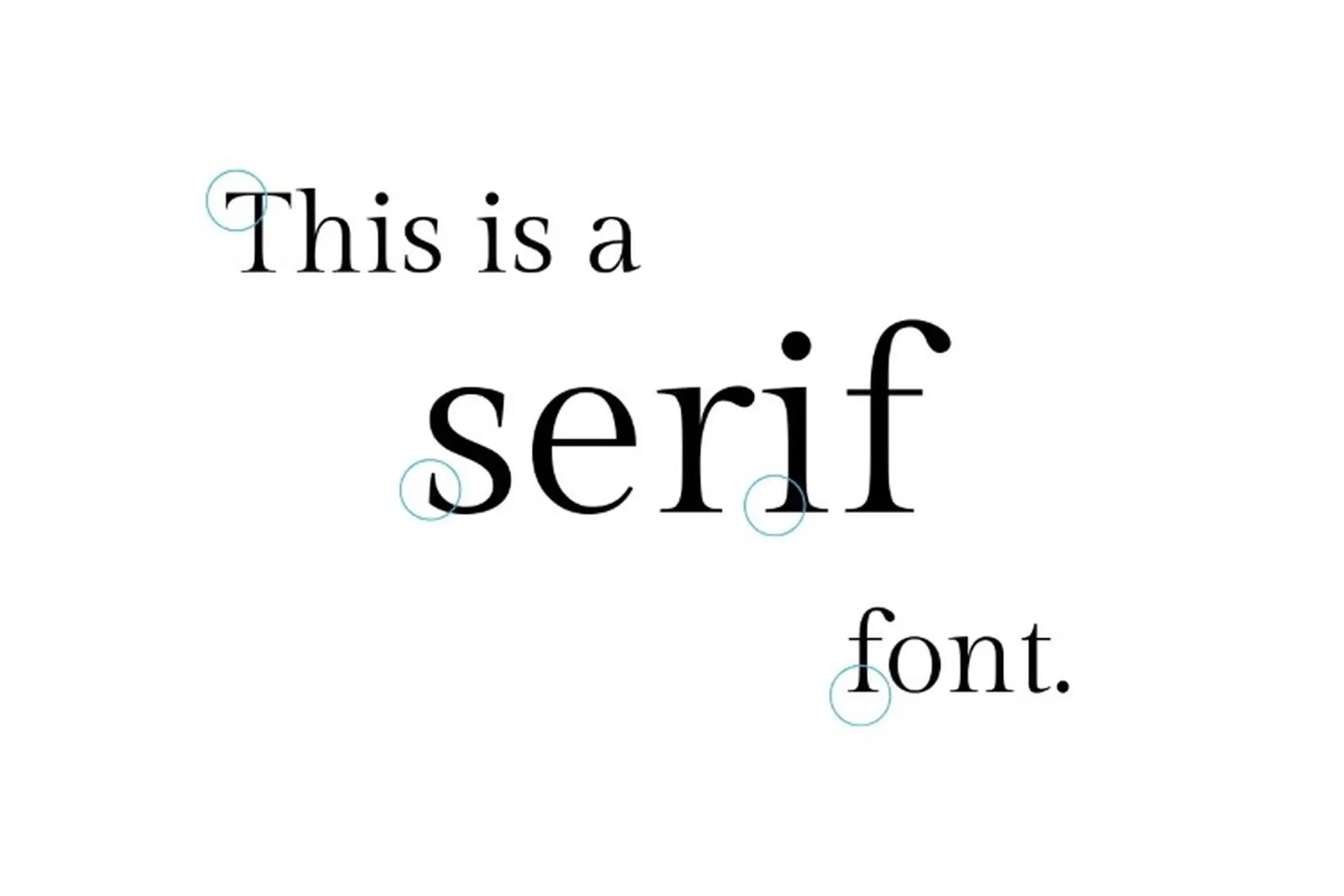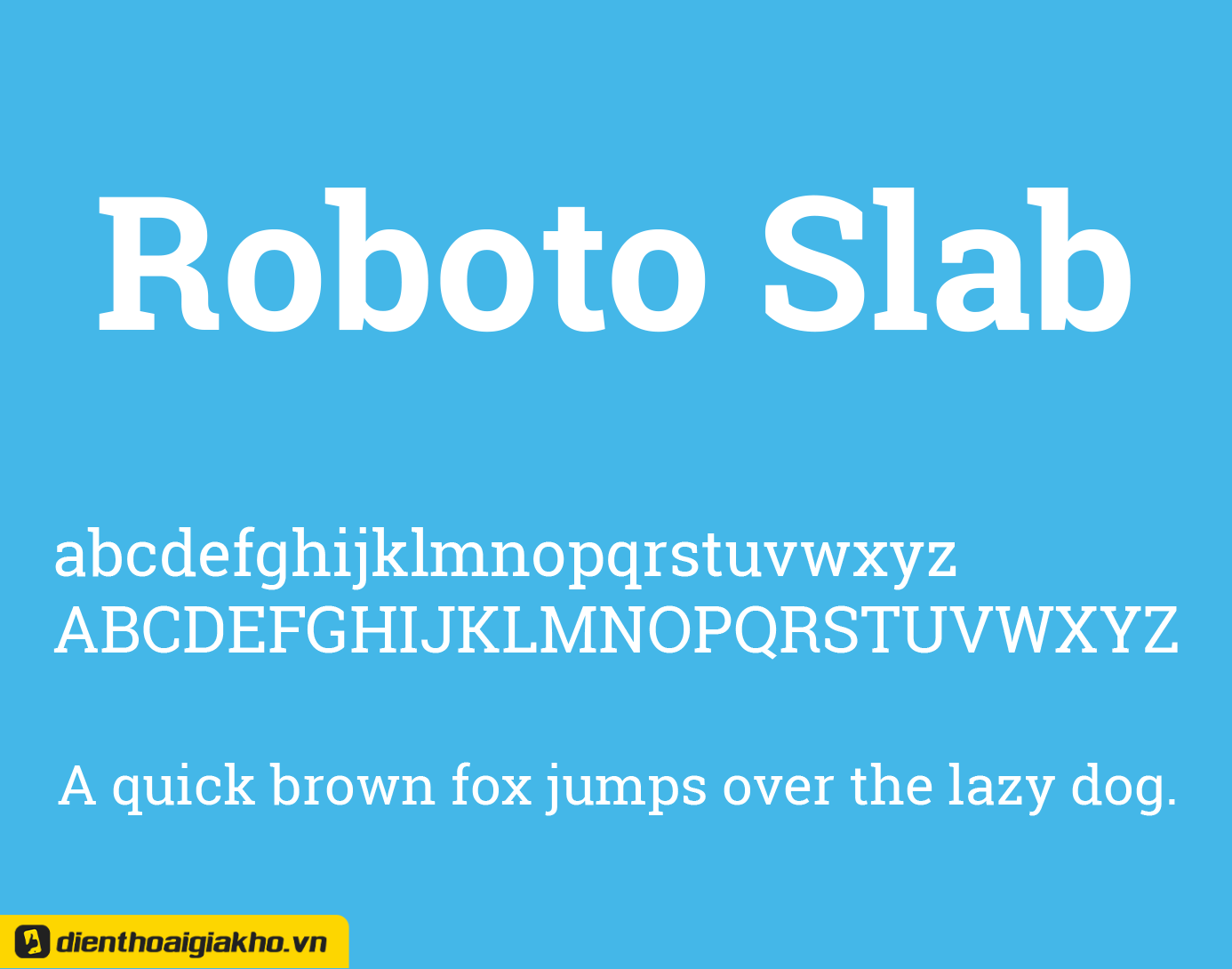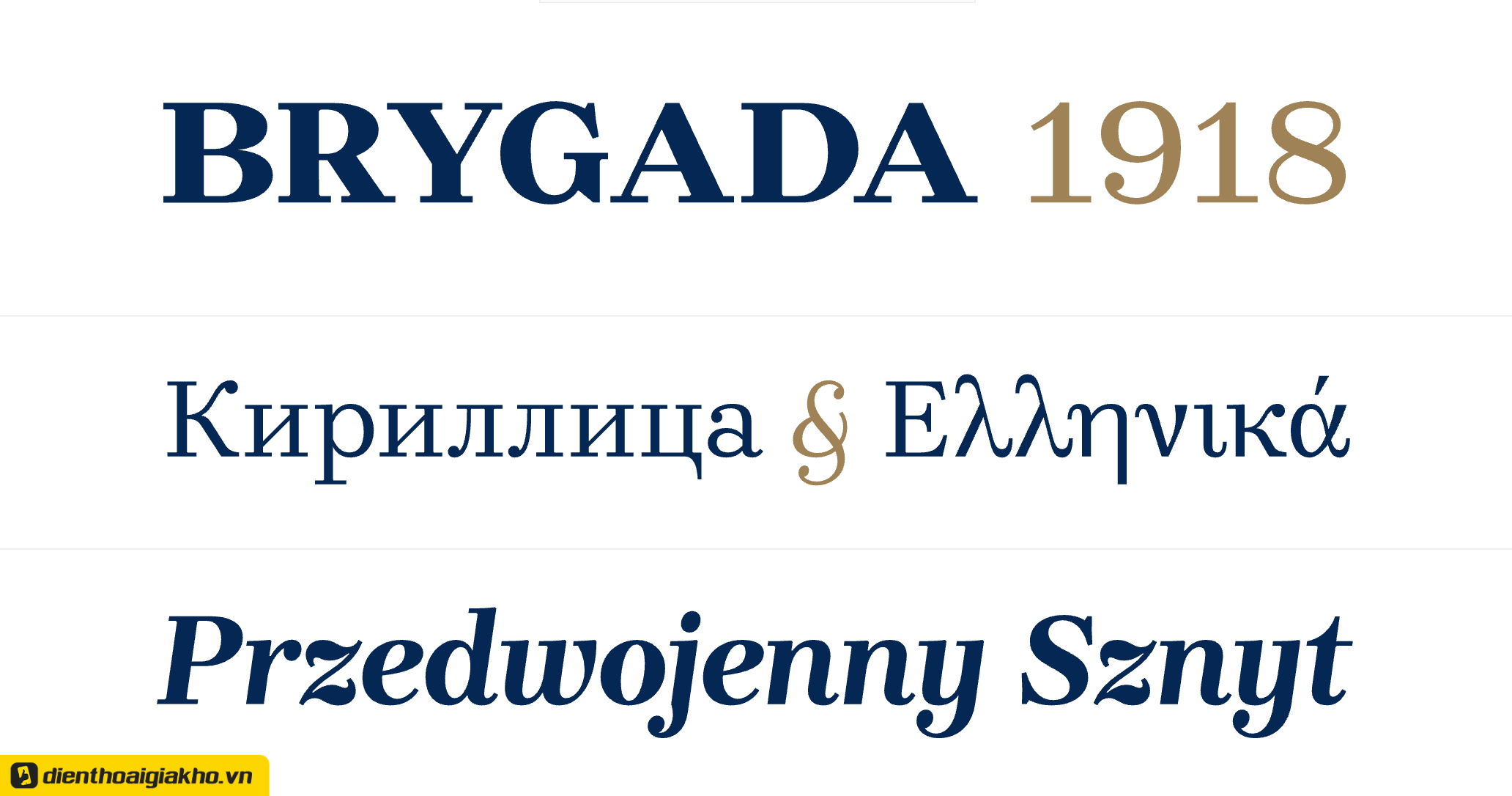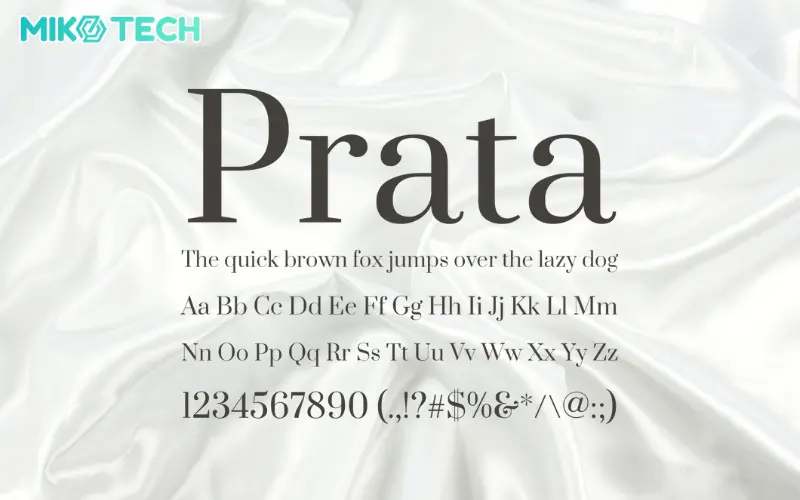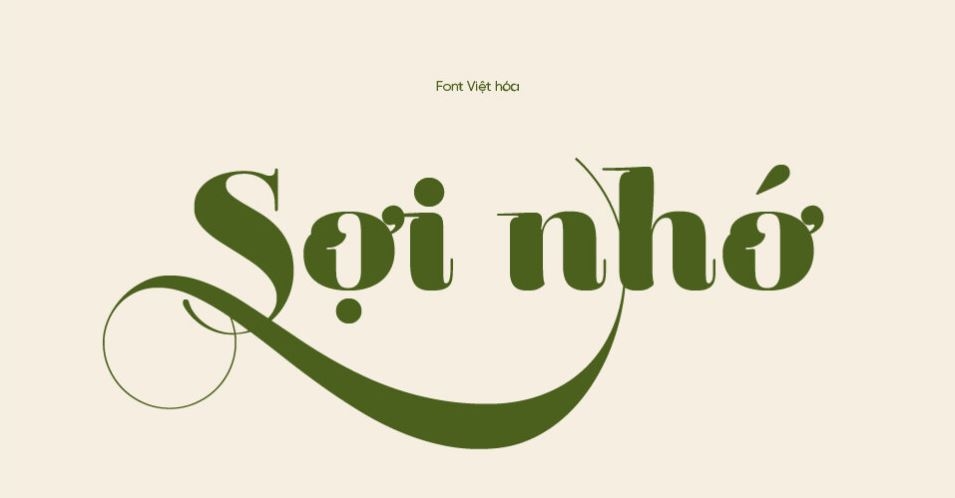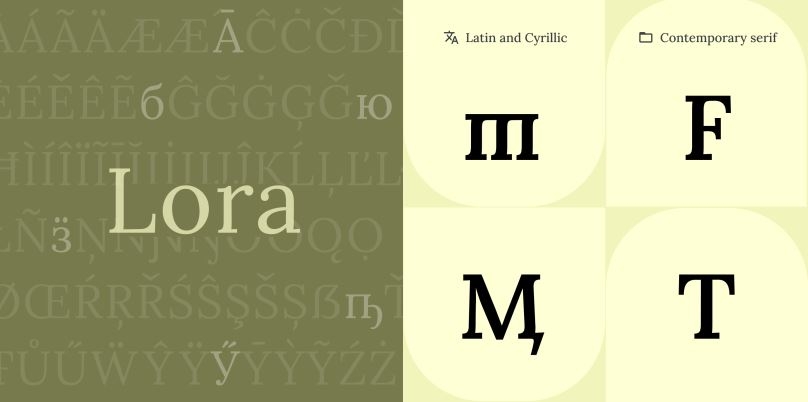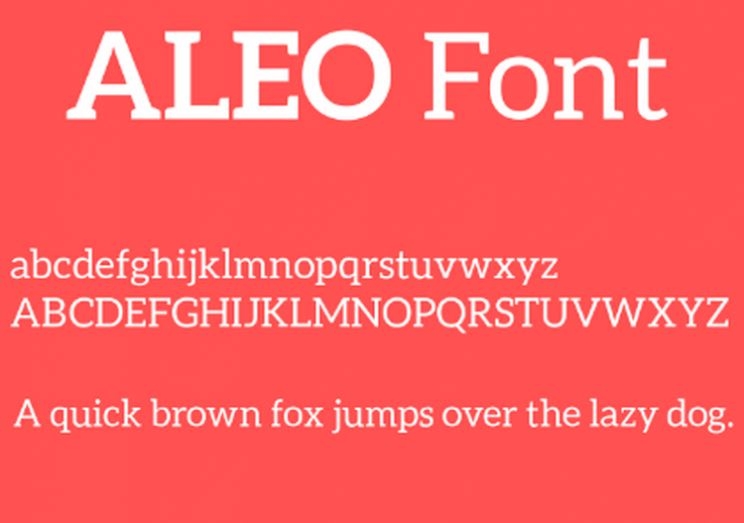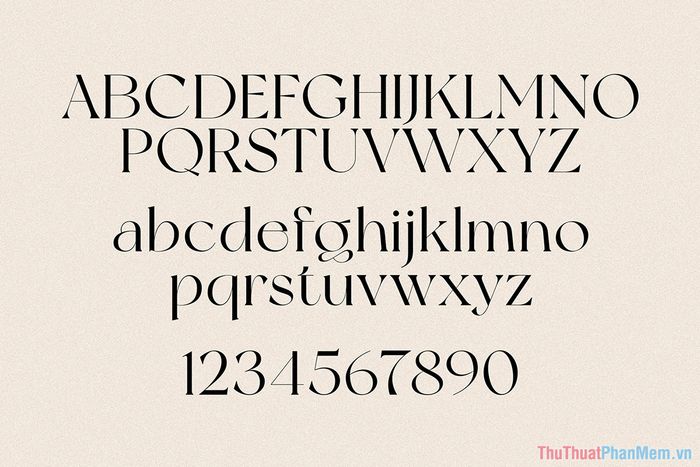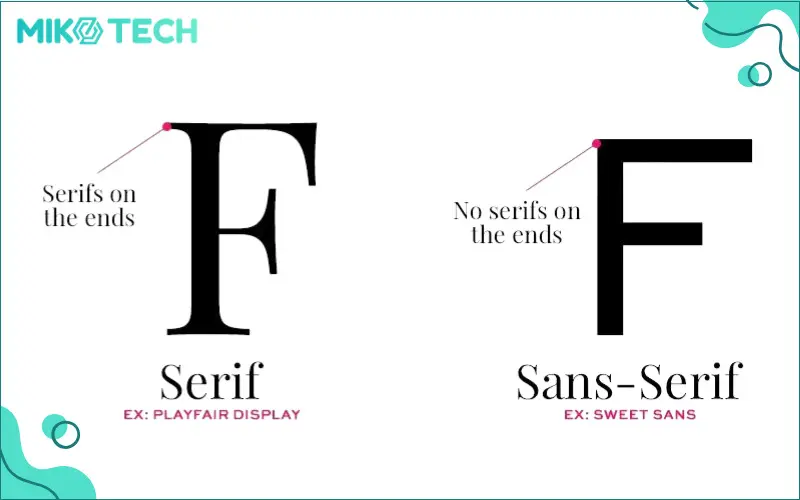
Font Chữ Có Chân Đẹp
Font chữ có chân (serif) từ lâu đã trở thành lựa chọn quen thuộc trong thiết kế đồ họa, ấn phẩm và cả nội dung số nhờ vẻ đẹp trang nhã và tính ứng dụng cao. Không chỉ giúp tăng tính thẩm mỹ, font chữ có chân còn tạo cảm giác chuyên nghiệp, dễ đọc và truyền tải thông điệp hiệu quả. Trong bài viết này, chúng ta sẽ cùng tìm hiểu về các loại font chữ có chân đẹp, cách lựa chọn, tải về, ứng dụng hiệu quả cũng như điểm qua những font chữ có chân Việt hóa miễn phí và nổi bật nhất dành cho thiết kế, trình chiếu, logo… Hãy cùng khám phá để tìm ra lựa chọn phù hợp cho dự án của bạn!
Font Chữ Có Chân Đẹp
Font chữ có chân, hay còn gọi là serif, luôn giữ một vị trí đặc biệt trong thế giới thiết kế đồ họa và văn bản. Với khoảng 490 mẫu font khác nhau, các font này không chỉ mang đến sự tinh tế mà còn tạo cảm giác truyền thống và chuyên nghiệp. Trong số đó, một số font Việt hóa nổi bật như 1FTV VIP Brilon và 1FTV VIP Melista Italic, được giới thiệu vào năm 2025, cho thấy sự đổi mới trong thiết kế chữ.
Các mẫu font chữ có chân phổ biến như Reina, Barmbrack, hay Playfair Display lại khẳng định độ phổ biến của chúng trong giới thiết kế. Các kiểu chữ này không chỉ đẹp mắt mà còn dễ dàng sử dụng trong nhiều dự án khác nhau. Bên cạnh đó, những font chữ như Garamond và Didot LT Std Italic tiếp tục giữ vững vị trí của mình nhờ vào sự thanh thoát và sang trọng.
Việc sử dụng font chữ có chân trong các thiết kế không chỉ giúp truyền tải nội dung một cách hiệu quả mà còn nâng cao tính thẩm mỹ cho sản phẩm. Khi kết hợp với các font chữ hiện đại, chúng mang đến sự hài hòa và phong cách riêng cho các tác phẩm sáng tạo.
Kiểu chữ có chân đẹp mắt tinh tế
Các Loại Font Chữ Có Chân Đẹp
Trong thế giới thiết kế đồ họa, font chữ có chân (serif) luôn giữ một vị trí đặc biệt nhờ vẻ đẹp cổ điển và trang trọng của nó. Với các kiểu chữ như Playfair Display, Garamond, hay Didot LT Std Italic, font serif đem đến sự tinh tế, phù hợp cho các thương hiệu muốn thể hiện sự lịch sự và chuyên nghiệp. Một số mẫu font nổi bật khác có thể kể đến như Lora, Prata hay Cormorant, mỗi loại đều mang phong cách riêng, giúp cho nội dung trở nên thu hút hơn.
Ngoài ra, các mẫu font chữ Việt hóa cũng không kém phần đa dạng. Một số font tiêu biểu như TH HC Calvous hay TH Luxury 8 không chỉ đẹp mắt mà còn phù hợp hơn với văn hóa và thị hiếu của người Việt. Khi sử dụng những font chữ này trong thiết kế poster hay tài liệu, chắc chắn sẽ làm tăng giá trị thẩm mỹ và tạo ấn tượng tốt cho người xem.
Khả năng dễ đọc và sự truyền tải cảm xúc chính là yếu tố giúp font chữ có chân trở thành lựa chọn lý tưởng cho nhiều loại hình thiết kế. Hãy thử nghiệm với những font chữ này để nâng tầm dự án của bạn nhé!
Font chữ có chân đẹp đa dạng phong cách tinh tế
Font Chữ Có Chân Đẹp Cho Thiết Kế
Font chữ có chân luôn mang lại một nét thanh lịch và sự sang trọng cho mọi thiết kế. Trong số đó, Playfair Display là một lựa chọn nổi bật, được sản xuất bởi Claus Eggers Sørensen. Font này sở hữu sự tinh tế với chiều sâu và tính tương phản cao, giúp thu hút ánh nhìn và tạo ấn tượng mạnh mẽ. Đây chính là lý do Playfair Display thường được ưa chuộng trong các dự án thiết kế cao cấp như poster, sách hay thương hiệu.
Ngoài ra, bộ 3 font NVN January cũng đáng để khám phá, cùng với các font khác như Garamond, Didot LT Std Italic, và Lora. Những font chữ này không chỉ mang lại vẻ đẹp cổ điển mà còn có độ dễ đọc cao, rất thích hợp cho những thiết kế liên quan đến thẩm mỹ và mỹ phẩm.
Một vài cái tên khác như Aire Roman Std với những nét mảnh mai, hay TH Retalin Regular thanh thoát cũng góp phần làm phong phú thêm lựa chọn cho các nhà thiết kế. Với sự đa dạng và phong phú của font chữ có chân, chắc chắn rằng việc lựa chọn sẽ không bao giờ khiến bạn thất vọng.
Font chữ có chân đẹp cho mọi dự án thiết kế
Download Font Chữ Có Chân Đẹp
Nếu bạn đang tìm kiếm những font chữ có chân đẹp để làm nổi bật các thiết kế của mình, thì bạn không nên bỏ qua bộ sưu tập font phong phú với hơn 490 loại này. Font chữ có chân (Serif) thường được yêu thích vì những nét gạch nhỏ giúp văn bản trở nên ổn định và dễ đọc hơn. Điều này đặc biệt quan trọng trong việc thiết kế các tài liệu, sách, hay tạp chí.
Năm 2025 đánh dấu sự ra mắt của nhiều font Việt hóa mới, như 1FTV VIP Brilon và 1FTV VIP Melista Italic. Những mẫu font này không chỉ tôn lên vẻ đẹp của chữ viết mà còn tạo cảm giác trang trọng cho bất kỳ thiết kế nào. Trong số các font nổi bật, có thể kể đến Reina, Barmbrack, và Tropical Qebalon, đều rất phù hợp để sử dụng trong các dự án sáng tạo.
Người dùng có thể dễ dàng tải về những font chữ Việt hóa đẹp mắt này từ nhiều trang web miễn phí. Hãy tận dụng những mẫu font như Playfair Display hay Garamond để nâng tầm thiết kế của bạn, và khám phá thêm hàng loạt lựa chọn khác như font máy đánh chữ cổ điển hay những mẫu sang trọng, phù hợp với nhiều phong cách khác nhau.
Kiểu chữ chân đẹp miễn phí
Cách Chọn Font Chữ Có Chân Đẹp
Khi chọn font chữ có chân, như Barmbrack, bạn nên chú ý đến nguồn cảm hứng và đặc điểm của nó. Font Barmbrack mang đậm phong cách showcard lettering với các đường nét phóng khoáng, tạo sự nổi bật và ấn tượng. Bên cạnh đó, nó còn mang đến cảm giác sang trọng và cổ điển, rất phù hợp cho các sản phẩm cao cấp.
Một mẹo hay là kết hợp giữa font có chân (serif) và font không chân (sans-serif). Việc phối hợp này tạo ra sự tương phản rõ rệt, khiến cho thiết kế trở nên sinh động hơn. Hãy nhớ rằng sự khác biệt giữa hai kiểu chữ sẽ giúp thu hút sự chú ý của người xem.
Những font chữ có chân phổ biến như Times New Roman và Georgia không chỉ dễ đọc mà còn mang lại cảm giác quen thuộc cho người dùng. Đặc biệt, trong thiết kế poster, font chữ serif thể hiện được sự trang nghiêm và đẳng cấp. Nhờ vào tính dễ đọc và phong cách độc đáo, font chữ có chân luôn là lựa chọn hàng đầu cho nhiều nhà thiết kế hiện nay.
Font chữ có chân đẹp cho mọi thiết kế
Font Chữ Có Chân Đẹp Miễn Phí
Nếu bạn đang tìm kiếm những font chữ có chân đẹp mắt miễn phí, kho tài nguyên font chữ Việt hóa 1FTV VIP là một địa chỉ tuyệt vời. Nơi đây hiện có khoảng 490 font chữ, với những mẫu font nổi bật như Brilon, Melista Italic và Astrite Linery, hứa hẹn mang đến sự đa dạng cho thiết kế của bạn.
Trong số những font chữ có chân phổ biến, không thể không kể đến Reina, Barmbrack, hay Lora. Những font như Playfair Display và Garamond không chỉ đẹp mà còn phù hợp với nhiều loại nội dung, từ báo chí cho đến tạp chí. Với thiết kế tinh tế, những font này sẽ tạo ra hiệu ứng thẩm mỹ ấn tượng cho các bản in và hình ảnh số.
Bên cạnh đó, bạn cũng có thể khám phá các font vui tươi như Hangout, hay những mẫu cổ điển như Clear Text và Minguwest. Tất cả đều mang đến cho bạn một kho font chữ chất lượng cao, hoàn toàn miễn phí, giúp bạn thoải mái sáng tạo mà không cần lo lắng về bản quyền.
Font chữ có chân đẹp miễn phí tải về ngay
Font Chữ Có Chân Việt Hóa Đẹp
Font chữ có chân (hay còn gọi là font chữ serif) không chỉ mang lại vẻ đẹp cổ điển, mà còn thể hiện sự trang trọng và chuyên nghiệp trong thiết kế. Hiện nay, Việt Nam có nhiều bộ font chữ có chân được việt hóa, phục vụ cho nhu cầu sáng tạo của các nhà thiết kế. Điển hình như font 1FTV VIP Brilon hay 1FTV VIP Melista Italic, cả hai đều được cập nhật gần đây, phù hợp với nhiều phong cách thiết kế từ hiện đại đến cổ điển.
Ngoài ra, những font chữ như Playfair Display, Garamond hay Lora cũng rất được ưa chuộng. Chúng không chỉ đẹp mắt mà còn dễ đọc, phù hợp cho cả báo, tạp chí lẫn các bài post trên mạng xã hội. Không thể không nhắc đến kho font Việt hóa chất lượng cao từ các nguồn như Taifontviethoa.com, nơi bạn có thể tải miễn phí hàng trăm mẫu font khác nhau.
Việc sử dụng các font chữ có chân với tiếng Việt chuẩn không chỉ giúp tăng tính thẩm mỹ mà còn nâng cao trải nghiệm người đọc. Hướng dẫn cài đặt và sử dụng những font chữ này trên các phần mềm như Photoshop hay Illustrator rất đơn giản, giúp bạn dễ dàng thực hiện những mẫu thiết kế ấn tượng.
Font chữ có chân Việt hóa đẹp mắt tinh tế.
Font Chữ Serif Đẹp
Phông chữ serif luôn có một sức hút đặc biệt trong thế giới thiết kế và typography. Năm 2025, nhiều phông chữ serif nổi bật đã xuất hiện, đáp ứng nhu cầu đa dạng của cả các nhà thiết kế chuyên nghiệp lẫn người dùng thông thường. Một số font chữ nổi bật nhất có thể kể đến như SVN-Times New Roman, iCiel Garamond và UTM. Những phông chữ này không chỉ cổ điển mà còn mang phong cách riêng biệt, tạo nên sự khác biệt trong bất kỳ dự án nào.
Thêm vào đó, phông chữ như Lora và Playfair Display mang đến sự hiện đại và tinh tế, với độ tương phản hợp lý giúp nâng cao tính dễ đọc. Vogue đã chọn Didot cho thiết kế của mình, minh chứng cho sức mạnh vượt thời gian của các font chữ serif. Từng nét chữ thanh lịch không chỉ truyền tải thông điệp mà còn tạo ra một phong cách nghệ thuật ấn tượng.
Từ việc lựa chọn font cho sách tới các dự án thiết kế logo, phông chữ serif đóng vai trò thiết yếu trong việc thể hiện phong cách và cá tính của thương hiệu. Dù bạn tìm kiếm sự cổ điển hay hiện đại, chắc chắn rằng sẽ có một kiểu serif phù hợp với nhu cầu của bạn trong bộ sưu tập font chữ đa dạng hiện nay.
Kiểu chữ Serif thanh lịch sang trọng cuốn hút
Top Font Chữ Có Chân Đẹp
Font chữ có chân (serif) luôn được ưa chuộng bởi vẻ đẹp sang trọng và lịch lãm của nó. Một số mẫu font chữ nổi bật mà bạn có thể tham khảo như Reina, Barmbrack, và Yeseva One. Những font này không chỉ dễ đọc mà còn mang đậm tính nghệ thuật, rất thích hợp cho các thiết kế in ấn hay trang web.
Bên cạnh đó, các font truyền thống như Times New Roman, Georgia và Garamond cũng luôn đứng vững trong lòng người thiết kế. Chúng được ưa chuộng không chỉ bởi vẻ đẹp mà còn vì tính ứng dụng cao, phù hợp cho nhiều loại văn bản khác nhau.
Nếu bạn đang tìm kiếm những mẫu font chữ có chân đẹp hơn, hãy thử Playfair Display hay Lora. Chúng mang lại cảm giác hiện đại hơn nhưng vẫn giữ được nét cổ điển mà serif thường có. Đặc biệt, với các bản Việt hóa như font máy đánh chữ cổ điển, bạn sẽ dễ dàng tìm được lựa chọn phù hợp cho dự án của mình. Đừng ngần ngại thử nghiệm với những kiểu chữ này để làm nổi bật thông điệp của bạn!
Top font chữ có chân đẹp và sang trọng
Font Chữ Có Chân Đẹp Dùng Trong Logo
Font chữ có chân từ lâu đã được biết đến như một lựa chọn tuyệt vời cho thiết kế logo, mang lại vẻ đẹp thanh lịch và chuyên nghiệp. Một trong những font nổi bật trong dòng chữ này là Playfair Display. Được phát triển bởi Claus Eggers Sørensen, font này không chỉ gây ấn tượng bởi sự khác biệt mà còn tạo cảm giác độc đáo cho thương hiệu.
Ngoài Playfair Display, Lora cũng là một sự lựa chọn đáng chú ý với sự tương phản vừa phải. Những đặc điểm này mang đến vẻ đẹp hiện đại, tinh tế và dễ đọc, là yếu tố quan trọng trong việc thiết kế logo. Không thể không nhắc đến Helvetica, một trong những phông chữ sans serif phổ biến nhất, được nhiều thương hiệu như Microsoft hay Jeep ưa chuộng.
Thêm vào đó, Choplin và Montserrat cũng là những font chữ rất đa dạng. Choplin với phong cách slab serif hình học tạo nên sự mạnh mẽ, còn Montserrat lại là lựa chọn lý tưởng cho bất kỳ thiết kế nào nhờ tính dễ đọc và biến hóa của nó. Tất cả những font chữ này đều góp phần tạo nên ấn tượng thương hiệu mạnh mẽ và thu hút.
Font chữ có chân đẹp cho logo thêm sang trọng